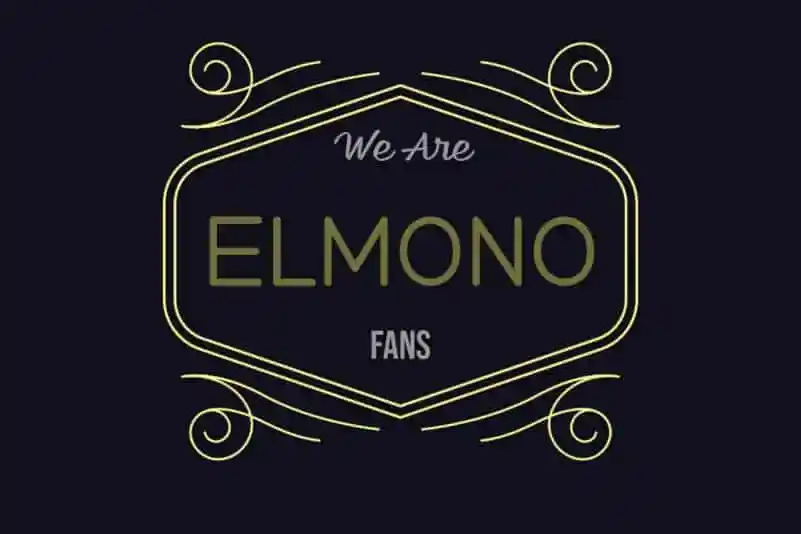
A fonte Elmono Sans Serif é uma escolha perfeita para designers que procuram uma tipografia fresca e moderna. Com linhas monolineares e um estilo grotesco-humanista, esta fonte traz uma dose de simplicidade e contemporaneidade aos projetos visuais. Ideal tanto para aplicar em trabalhos de marca, como logotipos, designs de casamentos ou postagens nas redes sociais, o Elmono Sans Serif também é um ótimo candidato para criar textura em embalagens de produtos, design gráfico, anúncios, etiquetas, fotografia e até mesmo rótulos de água sanitária. Seja você criando invitações ou cartões de visita para sua próxima exposição de arte, o Elmono Sans Serif é uma fonte versátil e atraente que fará seu trabalho efetivamente em qualquer projeto visual.